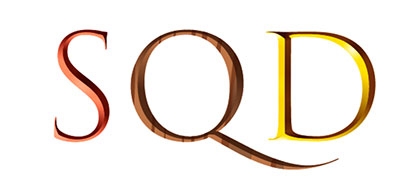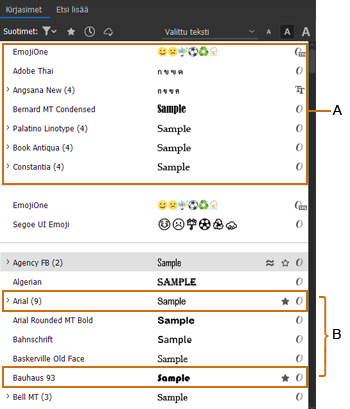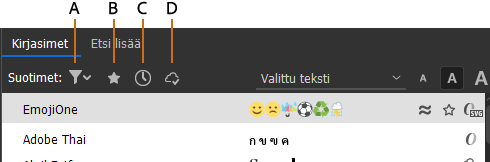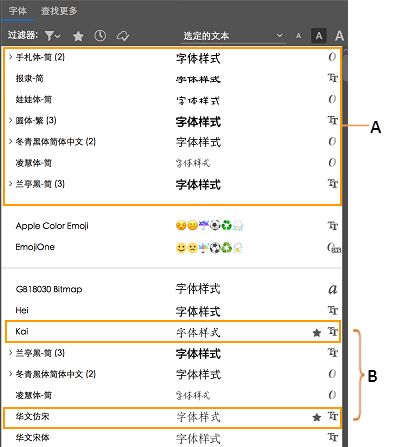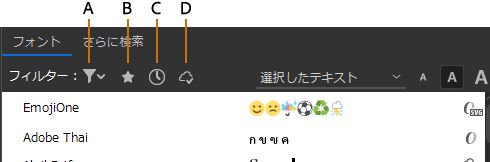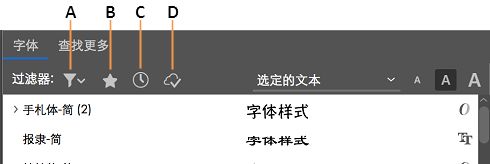
在 InCopy 中使用字体
关于字体
字体 是由一组具有相同粗细、宽度和样式的字符(字母、数字和符号)构成的完整集合,如 10 磅 Adobe Garamond 粗体。
字形(通常称为文字系列字体系列)是由具有相同整体外观的字体构成的集合,它们是专为一起使用而设计的,如 Adobe Garamond。
字体样式 是字体系列中单个字体的变体。通常,字体系列的罗马体普通(实际名称因字体系列而异)是基本字体,其中可能包括一些文字样式,如常规、粗体、半粗体、斜体和粗体斜体。
字体类型
可以在“字符”面板的字体系列菜单和字体样式菜单中查看某一字体的样本,也可以通过应用程序中其他能够选择字体的区域进行查看。下列图标说明了不同类型的字体:
• OpenType
• OpenType SVG
• Type 1
• TrueType
• Adobe Fonts
• 多模字库
• 复合
可以关闭预览功能,或更改“文字”首选项中字体名称或字体样本的磅大小。
如果在 InCopy 中有两种或更多种现用字体并且它们使用相同的系列名称,但具有不同的 Adobe PostScript 名称,则这些字体在 InCopy 中可用。在菜单中,重复的字体在后面的括号中注有其字体技术的缩写形式。例如,Helvetica TrueType 字体显示为“Helvetica (TT)”,Helvetica PostScript Type 1 字体显示为“Helvetica (T1)”,Helvetica OpenType 字体显示为“Helvetica (OTF)”。如果两种字体具有相同的 PostScript 名称,且其中一种字体的名称中包含 .dfont,则系统会使用另一种字体。
OpenType 字体
OpenType 字体使用一个适用于 Windows® 和 Macintosh® 计算机的字体文件,因此,您可以将文件从一个平台移到另一个平台,而不用担心字体替换或其它导致文本重新排列的问题。它们可能包含一些当前 PostScript 和 TrueType 字体不具备的功能,如花饰字和自由连笔字。
注意:
OpenType 字体显示 图标。
使用 OpenType 字体时,您可以自动替换文本中的替代字形,如连字、小型大写字母、分数字以及旧式的等比数字。
常规字体(左)和 OpenType 字体(右)
A. 序数字 B. 自由连笔字 C. 花饰字
OpenType 字体可能包括扩展的字符集和版面特征,用于提供更丰富的语言支持和高级的印刷控制。在应用程序字体菜单中,包含中欧 (CE) 语言支持的 Adobe OpenType 字体包括单词"Pro"作为字体名称的一部分。不包含中欧语言支持的 OpenType 字体被标记为"Standard"并带有"Std"后缀。所有 OpenType 字体也可以与 PostScript Type 1 和 TrueType 字体一起安装和使用。
应用 OpenType 字体属性
使用“字符”面板或“控制”面板应用 OpenType 字体属性
使用“字符”面板或“控制”面板可对文本应用 OpenType 字体属性,如分数字和花饰字。
1. 选择文本。
2. 在“字符”面板或“控制”面板中,确保选择了 OpenType 字体。
3. 从“字符”面板菜单中选择“OpenType”,然后选择一种 OpenType 属性,如“自由连笔字”或“分数字”。
当前字体不支持的功能显示在方括号中,例如 [花饰字]。
注意:
也可以在定义段落或字符样式时,选择 OpenType 字体属性。使用“样式选项”对话框中的“OpenType 功能”部分。
使用上下文菜单应用 OpenType 字体属性
使用上下文菜单可对选定文本应用适用的 OpenType 字体属性。
1. 选择文本。
2. 从弹出窗口选择一种 OpenType 属性,例如“序数字”或“分数字”。
注意:
如果您在选择文本或文本框架后看到一个徽章,请单击该徽章以查看 OpenType 属性列表。
OpenType 字体属性
如果您使用的是 OpenType 字体,则可以在设置文本格式或定义样式时,从“控制”面板或“字符”面板菜单中选择特定的 OpenType 功能。
注意:
OpenType 字体所提供的字体样式的数量和功能种类差异很大。如果某项 OpenType 功能不可用,则会在“控制”面板菜单中用方括号将其括起(如 [花饰字])。
自由连笔字
字体设计程序可能包含在任何情形下均不得打开的可选连笔字。选择该选项之后,就可以使用这些附加的可选连笔字(如果存在)。有关连笔字的更多信息,请参阅将连笔字应用于字母对
许多用于日文片假名的复合字符字形(如“me-toru”)和用于汉字复合词的复合字符字形(如“yuugenkaisha”),可以通过自由连笔字功能来访问。
分数字
当分数字可用时,系统会将以斜线分隔的数字(如 1/2)转换为分数字字符。
序数字
当序数字可用时,系统会采用上标字母格式表示序数字(如第一第二分别用 1st 和 2nd 表示)。系统还会对一些字母的上标 ao(西班牙语单词 segunda (2a) 和 segundo (2o) 中)进行适当排版。
花饰字
当花饰字可用时,系统会提供常规花饰字和上下文花饰字,这二者可能会包含替代大写字母和字尾替代字。
标题替代字
当标题替代字可用时,系统会激活用于大写标题的字符。在某些字体中,选择该选项为同时包含大、小写字母的文本设置格式,效果可能不理想。
上下文替代字
当上下文替代字可用时,系统会激活上下文连笔字和连接替代字。某些手写字形中会包括替代字符,用于提供更好的连接行为。例如,可以将单词“bloom”中的字母对“bl”连接起来,使其看起来更像手写体。此选项默认为已选中。
全部小型大写字母
对于包含真小型大写字母的字体,选择该选项会将字符转换为小型大写字母。有关更多信息,请参阅更改文字的大小写
斜线零
选择该选项后,所显示的数字 0 中会穿有一条斜线。在某些字体(特别是细长字体)中,很难区分数字 0 和大写字母 O
样式集
某些 OpenType 字体包含为获得美观效果而设计的替代字形集。风格组合是一组字形替代字,可以一次应用于一个字符,也可以应用于一段文本。如果选择其他风格组合,则会使用该组合中定义的字形,而不是字体的默认字形。如果将某风格组合中的一个字形字符与另一个 OpenType 设置结合使用,则该单个设置中的字形会覆盖字符集字形。可以使用“字形”面板查看每个集的字形。
位置格式
在一些草书体以及像阿拉伯语这样的语言中,字符的外观可能取决于它在单词中的位置。当字符出现在单词的开头(首字位置)、中间(中间字位置)或结尾(尾字位置)时,其格式可能会发生变化,并且当它单独出现(孤立位置)时,其格式也可能发生变化。选择一个字符,然后选择一个“位置格式”选项以正确地设置其格式。选择“常规格式”选项时插入常规格式的字符;选择“自动格式”选项时所插入字符的格式取决于字符在单词中的位置以及字符是否单独出现。
上标和下标
某些 OpenType 字体包含升高或降低的字形,它们均根据周围字符进行过适当调整。如果对于非标准分数字,OpenType 字体不包含这些字形,则可以考虑使用“分子字”和“分母字”属性。
分子字和分母字
某些 OpenType 字体只将基本分数字(如 1/2 或 1/4)转换为分数字字形,而不转换非标准分数字(如 4/13 或 99/100)。在上述情况下,可对这些非标准分数字应用“分子字”和“分母字”属性。
定宽,全高
对于全高数字,提供相同的宽度。此选项适合用于每一行数字都必须对齐的情况下(例如在表格中)。
变宽,变高
提供宽度、高度均有变化的数字。这一选项建议用于没有使用全部大写,而且具有古典和复杂外观的文本。
变宽,全高
提供宽度变化的全高数字。建议对使用全部大写的文本使用此选项。
定宽,变高
提供宽度固定且相等、高度变化的数字。如果既需要变高数字的标准外观又需要使它们逐栏对齐(如年度报告),则建议使用该选项。
默认数字样式
数字字形使用当前字体的默认数字样式。
使用等比公制字
使用等比公制字字体复合字符。
使用横排或直排假名(日文)
对于包含直排或横排排版的假名的字体,将提供最适合横排或直排设置的假名字形。
罗马斜体字
如果字体包含斜体字形,则会将等比罗马字形切换为斜体文字。
应用 OpenType 字形格式
“字形”面板包含很多可以应用于所选文本的选项,如“专业格式”或“JIS 90 格式”。
1. 选择“文字”>“字形”,以打开“字形”面板。
2. 选择您要应用字形格式的一个或多个字符。
3. 从“字形”面板菜单中选择一个选项,如“专业格式”或“JIS 90”。
OpenType SVG 字体
InCopy 支持类似彩色字体和 emoji 字体这样的 OpenType SVG 字体。OpenType SVG 字体在一种字形中提供了多种颜色和渐变。
OpenType SVG 字体:多种颜色和渐变
使用 Emoji 字体,您可以在文档中包含五颜六色、图形化的字符,例如表情符号、旗帜、路标、动物、人物、食物和地标等。使用 OpenType SVG emoji 字体(如 EmojiOne 字体),您可以通过一个或多个其他字形创建某些复合字形。例如,您可以创建国家/地区的旗帜,或者更改描述人物和身体部位(例如,双手和鼻子)的某种字形的肤色。
显示 EmojiOne SVG 字体字符的“字形”面板
要使用 OpenType SVG 字体,请执行以下步骤:
1. 使用“文字”工具创建文本对象。
2. 将字体设置为 OpenType SVG 字体。这些字体在字体列表中以 标记。
3. 使用“字形”面板选择特定字形。要查看“字形”面板,请选择文字 > 字形。或者,通过选择窗口 > 文字和表 > 字形,也可以打开“字形”面板。
创建复合字形
为了便于说明,我们以 EmojiOne 这种 OpenType SVG emoji 字体为例。您可以合成多个 EmojiOne OpenType SVG 字体字符来创建字形。
例如,您可以创建国家/地区的旗帜,或者更改单人或身体部位默认字符的肤色,颜色通常包括
某些 Type1 字体在文档中不可用。此外,在 Windows 中运行 InCopy 时,Mac OS 字体不可用。
Multiple 父字体
Multiple master 字体是可自定的 Type 1 字体,其字体特性是依据不同的设计侧重点(例如粗细、宽度、样式和视觉大小)来描述的。
某些 Multiple 父字体包括视觉大小方面的侧重点,使您能够使用经特别设计的、可在特定大小获得最佳可读性的字体。一般来说,与较大字体(如 72 磅)相比,较小字体(如 10 磅)的视觉大小在设计上具有以下特色:衬线和干线更粗、字符更宽、粗线和细线之间的对比更弱、X 高度更大、字母间距更宽松。
1. 选择“编辑”>“偏好设置”>“文字”(Windows) 或“InCopy”>“偏好设置”>“文字”(Mac OS)。
2. 选择“自动使用正确的视觉大小”,然后单击“确定”。